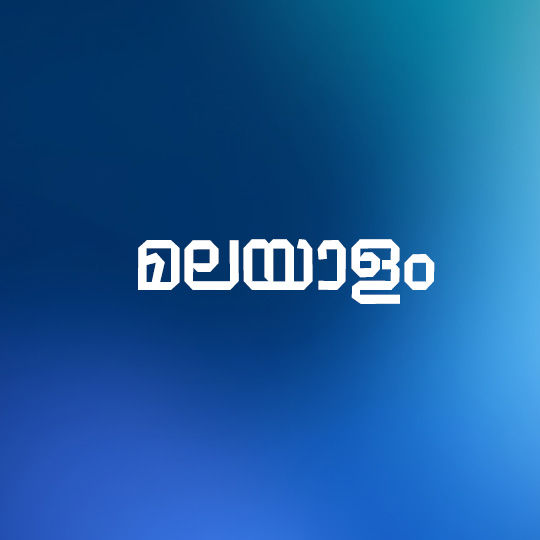
Kavya- Bold | Stylish Malayalam Poster Font
തലക്കെട്ടുകൾക്കും പോസ്റ്റർ ഡിസൈനുകൾക്കും ഒരുപോലെ അനുയോജ്യമായ ഒരു കണ്ടൻസ്ഡ് ബോൾഡ് ഫോണ്ടാണ് ML-KV-Kavya-CB. അക്ഷരങ്ങൾക്കിടയിലുള്ള കുറഞ്ഞ അകലവും ബോൾഡ് ആയ ശൈലിയും ഡിസൈനുകൾക്ക് കൂടുതൽ വ്യക്തതയും ഭംഗിയും നൽകുന്നു. കുറഞ്ഞ സ്ഥലത്ത് കൂടുതൽ കാര്യങ്ങൾ മനോഹരമായി അവതരിപ്പിക്കാൻ ഈ ഫോണ്ട് സഹായിക്കും.